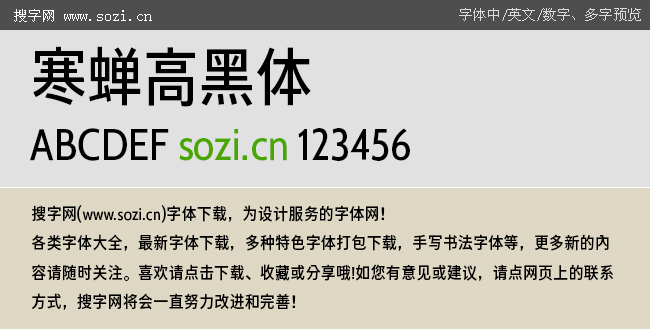
寒蟬高黑體
搜字網(wǎng)給大家提供一款寒蟬高黑體中文字體下載,寒蟬高黑體是基于未來(lái)熒黑、Cabin開(kāi)源字體融合手寫(xiě)感和部分舊字型的窄黑字體。同樣支持簡(jiǎn)體繁體,香港、臺(tái)灣常用字,目前僅有中黑體。適用于平面宣傳設(shè)計(jì)、網(wǎng)頁(yè)設(shè)計(jì)、海報(bào)設(shè)計(jì)等應(yīng)用。